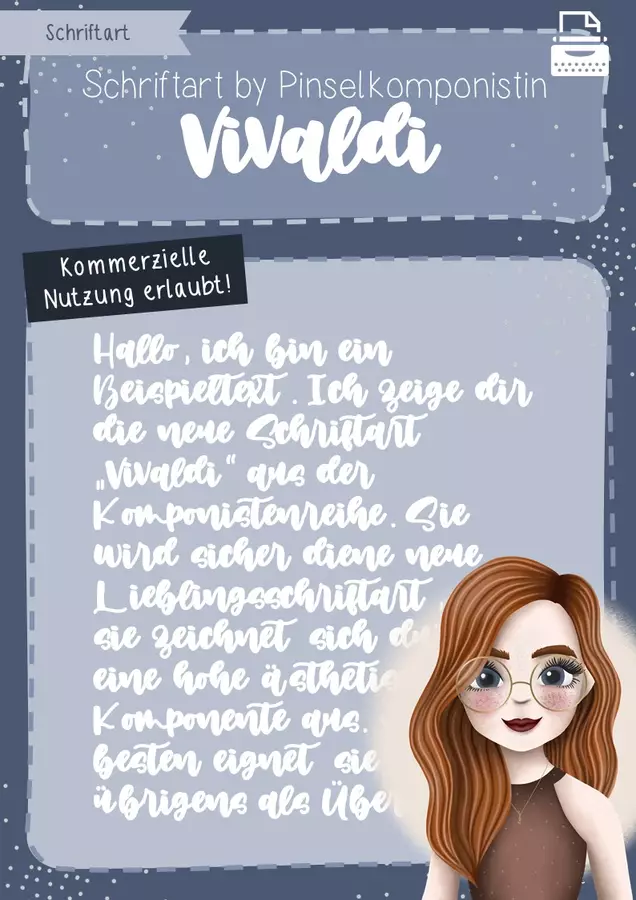
Hier kommt die fünfte und damit letzte Schriftart im Bunde der Komponistenreihe. Mit "Vivaldi" bekommt ihr zum Schluss nochmal ein wahres Überschriften-Schmankerl :-p
Schriftart by Pinselkomponistin: Vivaldi - Komponistenreihe